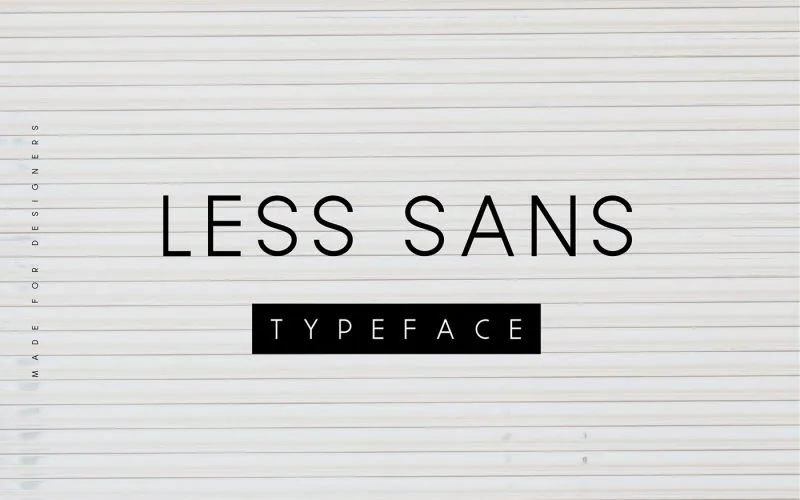
Less Sans Minimal Typeface – Download Grátis
Olá! Estou aqui para apresentar nossa nova criação ‘Less’ – uma fonte sans-serif que possui versatilidade suficiente para atender a diversas necessidades dos seus projetos de design. Seu carácter minimalista faz dele um amigo fiel, adaptável tanto ao texto pequeno quanto aos headlines poderosos. A ‘Less’ é uma tipografia desenvolvida com muito amor para atender quase todas as suas exigências de design. Feita a ponto mínimo possível, ela segue regras geométricas que criam formas e medidas perfeitamente harmonizadas. Este é um verdadeiro esforço em tornar o design mais puramente visual, eliminando tudo o que não seja essencial, deixando apenas o melhor da simplicidade. Sua elegância minimalista se combina com seu poderoso estilo, tornando-a a escolha perfeita para projetos que valorizam tanto a simplicidade quanto a força do design.
Designer: Beatrice